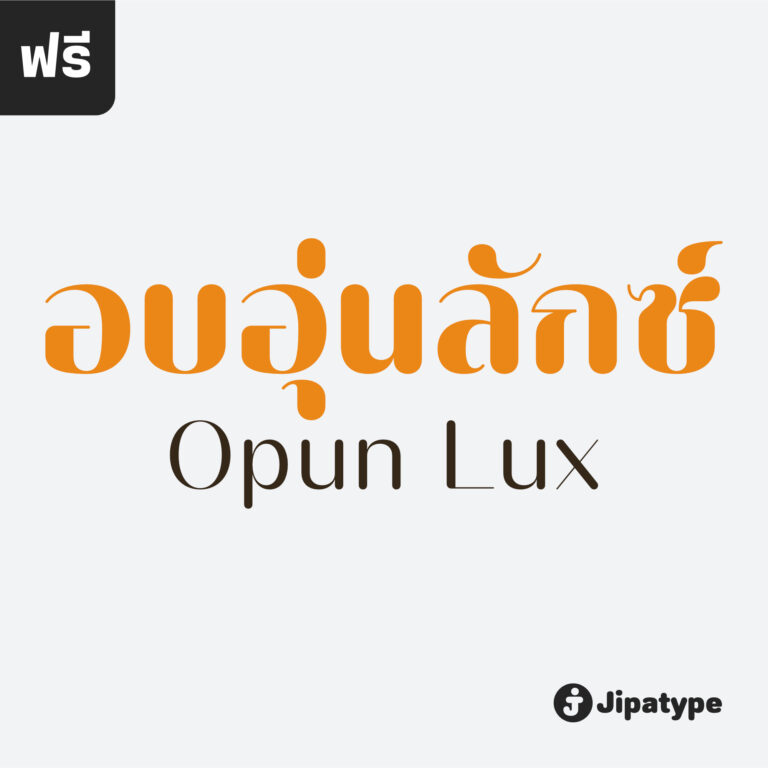
บรรณาธิการลูปเลส | Bunnathikarn Loopless
Bunnathikarn Loopless เป็นการต่อยอดดีไซน์จากตระกูล Bunnathikarn โดยปรับเปลี่ยนโครงสร้างอักษรไทยให้เป็นแบบไม่มีหัว เพื่อมอบภาพลักษณ์ที่ดูทันสมัย โฉบเฉี่ยว และมีความเป็นสากลมากยิ่งขึ้น เหมาะอย่างยิ่งสำหรับงานแบรนด์ดิ้งแฟชั่น สินค้าลักชัวรี่ สื่อไลฟ์สไตล์ หรือหัวข้อความ ที่ต้องการสะท้อนรสนิยมที่เหนือระดับและบุคลิกที่มั่นใจ
บรรณาธิการ | Bunnathikarn
Bunnathikarn เป็นแบบอักษรแซนเซอริฟ โดยมีชุดแบบอักษรไทยเป็นประเภทมีหัว ที่ผสมผสานความคลาสสิกเข้ากับความร่วมสมัยได้อย่างลงตัว โดดเด่นด้วยเส้นสายแบบ High Contrast ที่มีการตัดกันระหว่างเส้นหนาและเส้นบางอย่างชัดเจน ให้คาแรคเตอร์ที่ดูหรูหรา สง่างาม และมีความเฉียบคม แฝงไปด้วยความน่าเชื่อถือแบบมืออาชีพ
วรรณกรรม | Wannagam
Wannagam เป็นแบบอักษรเซอริฟที่ได้รับแรงบันดาลใจจากฟอนต์สุดคลาสิก Didot ตัวอักษรมีโครงสร้างที่ประณีตและสัดส่วนที่สมดุล เส้นสายของตัวอักษรให้ความรู้สึกสง่างาม แข็งแรง และน่าเชื่อถือ ในขณะเดียวกันยังคงไว้ซึ่งความอ่อนช้อยและความกลมกลืน เหมาะสื่อประชาสัมพันธ์ที่ต้องการความละเอียดอ่อน เช่น นิตยสาร ปกหนังสือ งานพิมพ์หรูหรา
อภิรมย์ | Aphirom
อภิรมย์ เป็นแบบอักษรคอนทราสต์แซนเซอริฟ มีโครงสร้างตัวอักษรที่แคบ มีเส้นแนวตั้งและแนวนอนเปรียบต่างกัน ให้ความรู้สึกผอมเพรียวและสวยงามเห็นแล้วรู้สึกได้ถึงความอภิรมย์ เหมาะสำหรับสื่อประชาสัมพันธ์ที่ต้องการสื่อสารเรื่องความงาม ความสุขสงบ ธรรมชาติ
รฦก (SOV_Raluek)
ฟอนต์รฦก ต้นทางจากแบบอักษรประดิษฐ์ เหมาะใช้เป็นพาดหัว
รัญจวน (MN Ran Juan)
อบอุ่นลักซ์ | Opun Lux
Opun Lux เป็นแบบอักษรแซนเซอริฟ ปลายเส้นมีความกลมมน มีความเปรียบต่างของขนาดเส้นนอนและเส้นตรง จากรูปร่างหน้าตาของแบบอักษรนี้ให้ความรู้สึกได้ถึงความหรูหรา งดงาม อ่อนช้อย ในขณะเดียวกันก็ให้ความรู้สึกเป็นมิตร และความอบอุ่น
เคอาร์ต ศุภฤกษ์ (Kart-Suparerk)
ฟอนต์งานแต่งมีหางฟอนต์อารมณ์ อ.จินดา เนื่องจำนงค์เจ้าของเพจ “อักษรตัวเขียน” ที่ผมก็เป็น FC ท่าน จนพัฒนาเป็น ศุภฤกษ์ ในปัจจุบันครับ แนวคิดในการออกแบบคือผมไม่สามารถสร้างหางประกอบได้เหมือนท่านเลยเอาหางที่พอคิดได้บรรจุลงในฟอนต์ซะเลยครับ
วิจิตรา | Wichittra
วิจิตรา เป็นแบบอักษรเซอริฟแบบแคบคอนทราสต์สูง ชื่อของแบบอักษรนี้มาจากชื่อทั่วไปของผู้หญิงไทย ซื่งมีความหมายว่า ‘สวย’ หรือ ‘งดงาม’ ออกแบบโดย : อานุภาพ ใจชำนาญ (Anupap Jaichumnan)สามารถทดลองใช้เวอร์ชันฟรีผ่านแอปฯ ของจิปาไทป์ได้ในเชิงพาณิชย์ ดูรายละเอียดและดาวน์โหลดแอปฯได้ที่ : jipatype.com
ทวิลักษณ์ เซอริฟ | Thawilak Serif
ขอแนะนำ Thawilak Serif แบบอักษรที่สวยงามและละเอียดอ่อนที่รวบรวมแก่นแท้ของความสง่างาม และความมั่นคง ด้วยคอนทราสต์สูงและรูปทรงที่กว้าง ฟอนต์นี้มีเสน่ห์เหนือกาลเวลาซึ่งจะสร้างความประทับใจให้กับผู้พบเห็นได้ไม่รู้ลืม Thawilak Serif คือตัวแทนแห่งความงามและความมั่นคง ไม่ว่าจะใช้ในสื่อสิ่งพิมพ์หรือสื่อดิจิทัล จะเพิ่มสัมผัสของความมีระดับและความน่าเชื่อถือให้กับโปรเจกต์ต่างๆ ไม่ว่าจะเป็นบทความ การสร้างแบรนด์ หรือบรรจุภัณฑ์ที่หรูหรา ออกแบบโดย : อานุภาพ ใจชำนาญ (Anupap Jaichumnan)สามารถทดลองใช้เวอร์ชันฟรีผ่านแอปฯ ของจิปาไทป์ได้ในเชิงพาณิชย์ ดูรายละเอียดและดาวน์โหลดแอปฯได้ที่ : jipatype.com